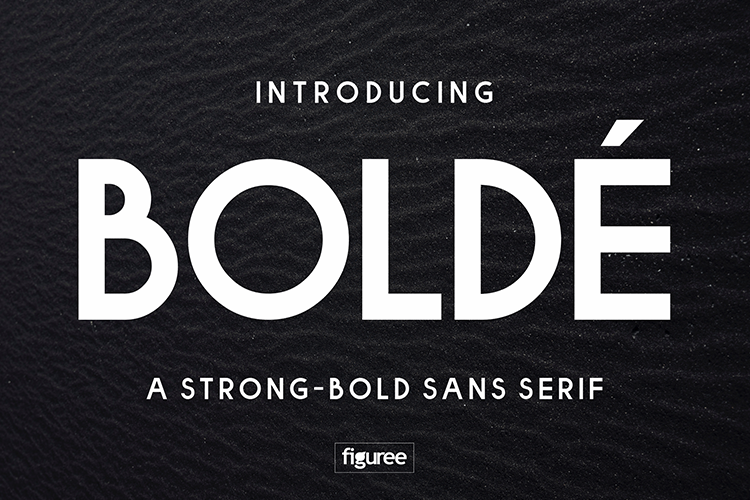
Bolde Sans Typeface – Fonte Grátis
Bolde Sans Typeface
Essa família de fontes sans serif é uma criação moderna e vintage apresentada pelo designer 24Design. Introduzimos a Bolde Font Family, que oferece um toque poderoso ao estilo do tipo serifado. Com linhas duros e curvas suaves, essa família de tipos se destaca por sua força dinâmica em qualquer aplicação. O design inclui uma ampla gama de estilos para atender a diversos usos, desde marcas ou logotipos até revistas ou filmes. A Bolde é perfeita para dar um toque inovador a seus trabalhos, seja no design gráfico ou na tipografia da web. Composta com um arco moderno e uma paleta de linhas duros, a Bolde está sempre à altura do seu projeto. A fonte está disponível em todas as categorias de fontes, e é perfeita para aqueles que buscam um estilo clássico com uma pegada futurista. Não hesite em experimentar e descubra o poder da Bolde Font Family.